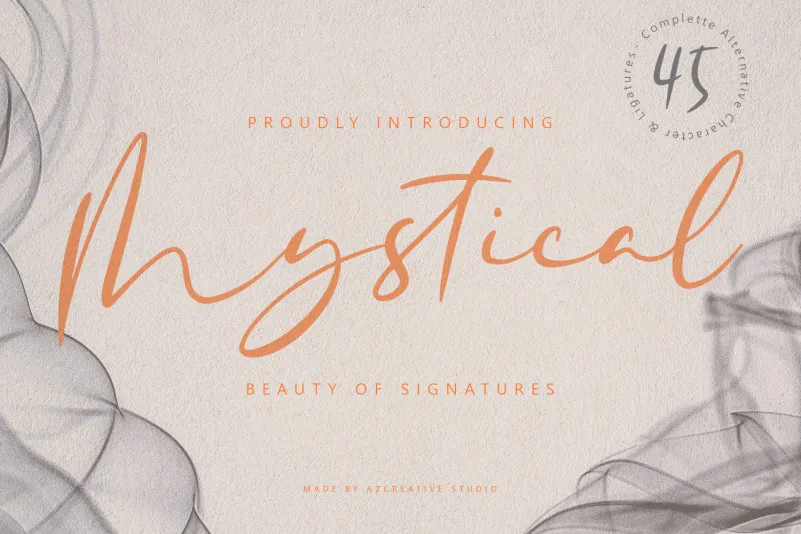
Mystical Font – Download Grátis
Esta é uma fonte script delicada e elegante, projetada para aqueles que desejam uma aparência refinada e alegre nos seus designs. Com sua codificação PUA, você pode acessar facilmente todos os sinais e swashes, criando textos cheios de vida e estilo. A fonte ‘Mystical’ transmite elegância e classe, perfeitamente adaptada para aquelas pessoas que buscam uma aparência sofisticada em seus trabalhos. Não apenas é um recurso prático e funcional, mas também uma escolha gráfica atraente capaz de revitalizar qualquer design. Seja para logotipos de marca, cartazes ou aplicativos digitais, esta fonte proporciona o toque final necessário para criar uma identidade visual única e impressionante. Em seu conjunto perfeito com um design elegante, Mystical é a escolha certa para designers que buscam uma ferramenta de alta qualidade para seus projetos.
Designer: azcreativestd